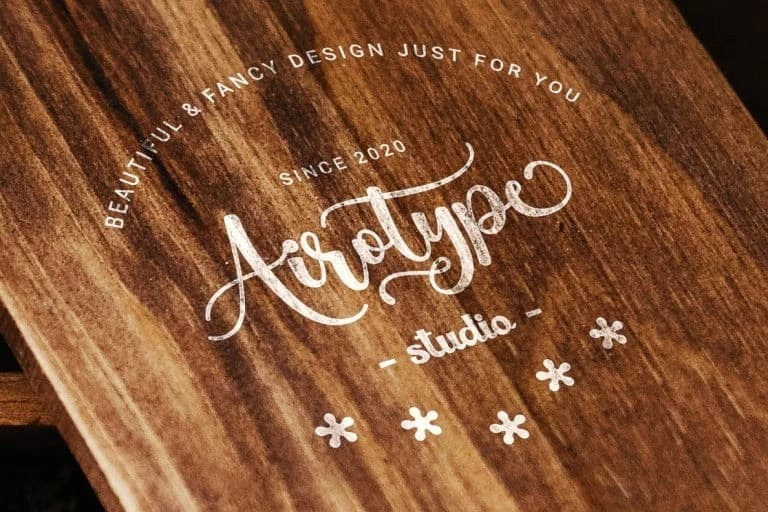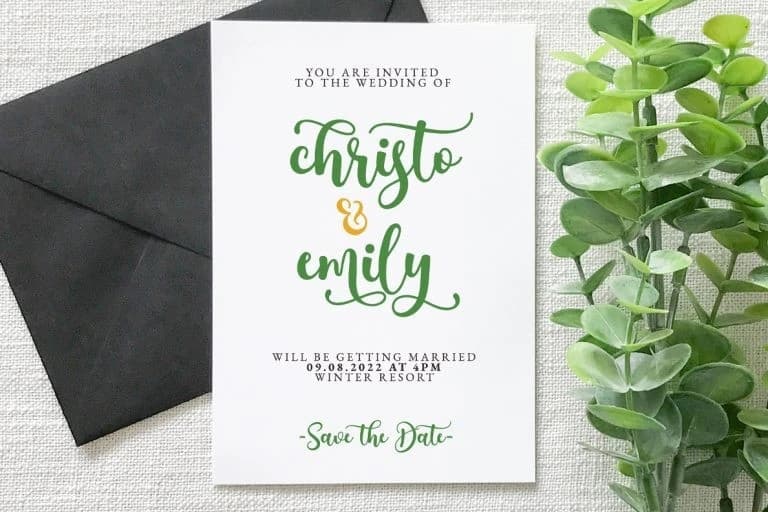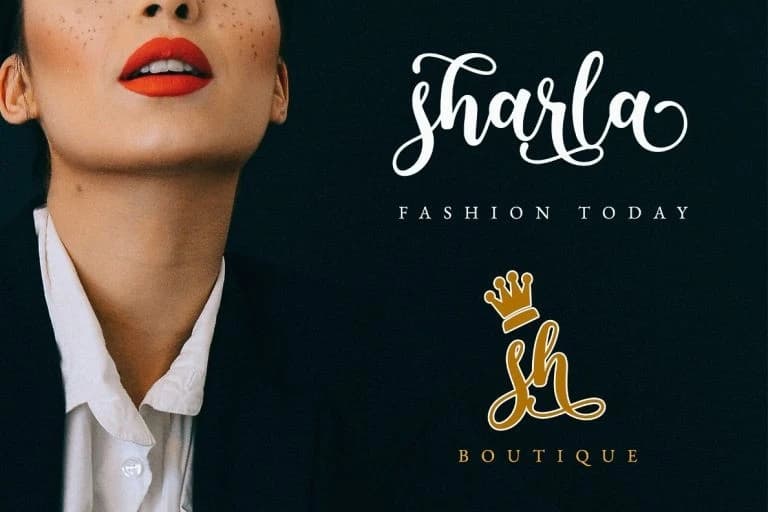
Patrick Airo Yazı Tipi
Patrick Airo Font kalın ve kıvrak bir script fontudur. Modern, zarif ve ince bir tarza sahiptir. Tasarımınızın güzelliğini artıracaktır. Patrick Airo Font, düğün tasarımı, davetiye, doğum günü, tişört tasarımı, el işi, çıkartma, sublimasyon ve daha birçok proje için mükemmel bir fonttur.
Patrick Airo Font kalın ve hareketli bir el yazısı fontudur. Modern, zarif ve ince bir tasarıma sahiptir. Tasarımınızın güzelliğini artıracaktır. Patrick, herhangi bir proje için mükemmel bir fonttur; örneğin düğün tasarımı, davetiye, doğum günü, tişört tasarımı, el işi, çıkartma, sublimasyon ve çok daha fazlası.